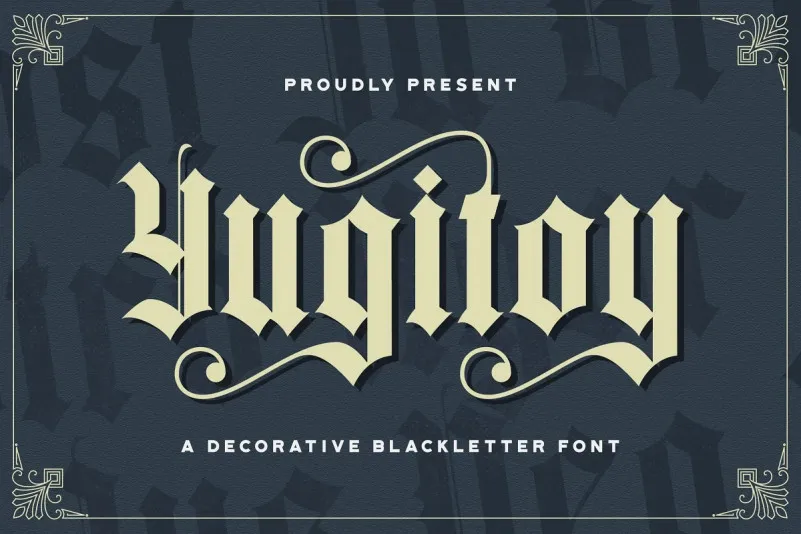
Yugitoy Blackletter Font – Download Grátis
A Yugitoy Blackletter Font é inspirada nos designs vintage encontrados em alguns cafés. Seus traços delicados e elegantes evocam o luxo e a sofisticação dos tempos vitorianos, criando um estilo único e deslumbrante. Esta fonte de tipo é perfeita para aqueles que buscam uma grata surpresa em cada página, seja ela um site, um projeto gráfico ou até mesmo um livro impresso. A Yugitoy traz um toque vintage a qualquer projeto sem se perder na estética moderna da Blackletter, resultando num resultado incrivelmente bem-sucedido em muitas situações diferentes. Ideal para usar em contexto de design gráfico moderno que busca uma mistura entre clássico e atual, ela oferece um toque único à sua identidade visual.